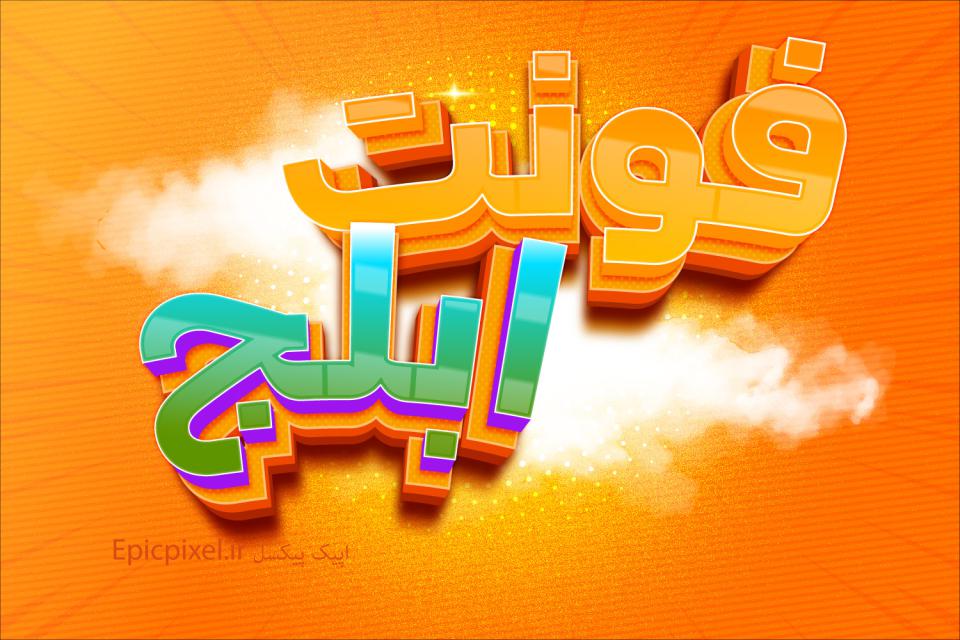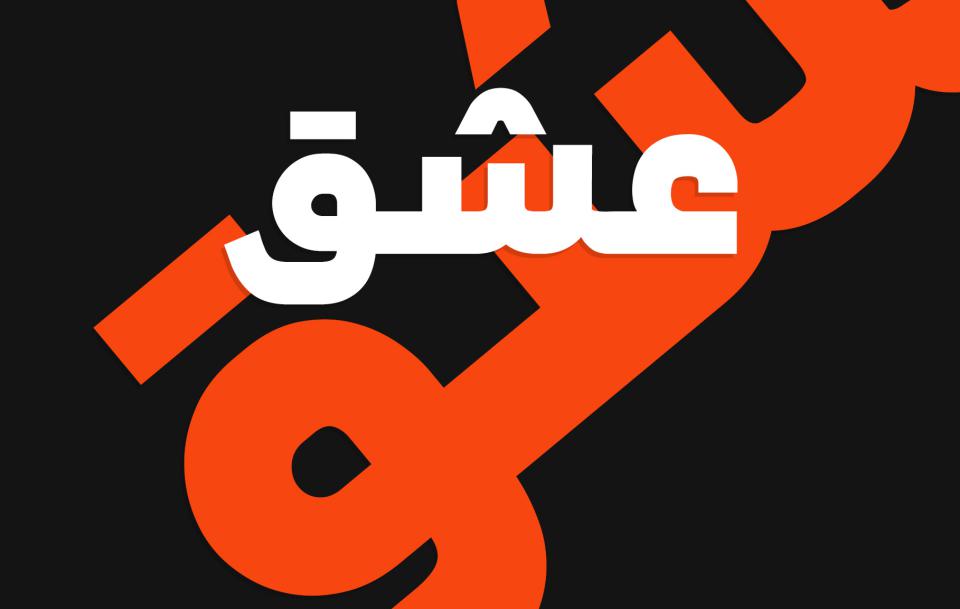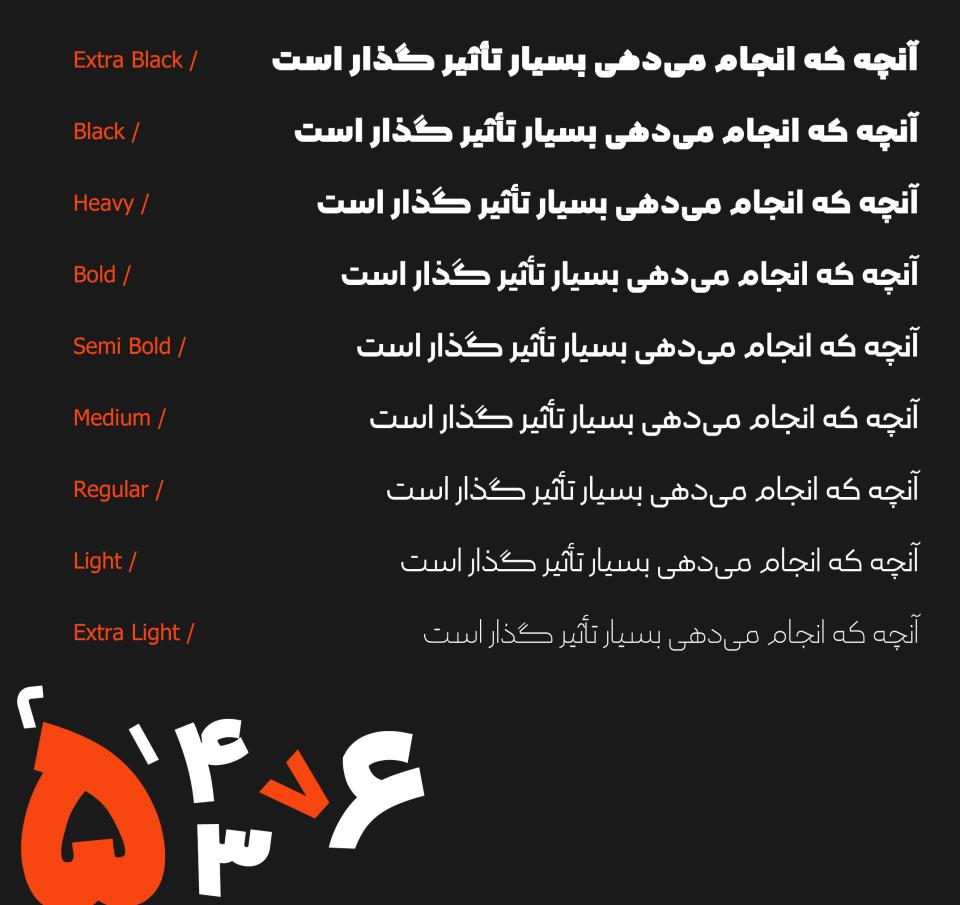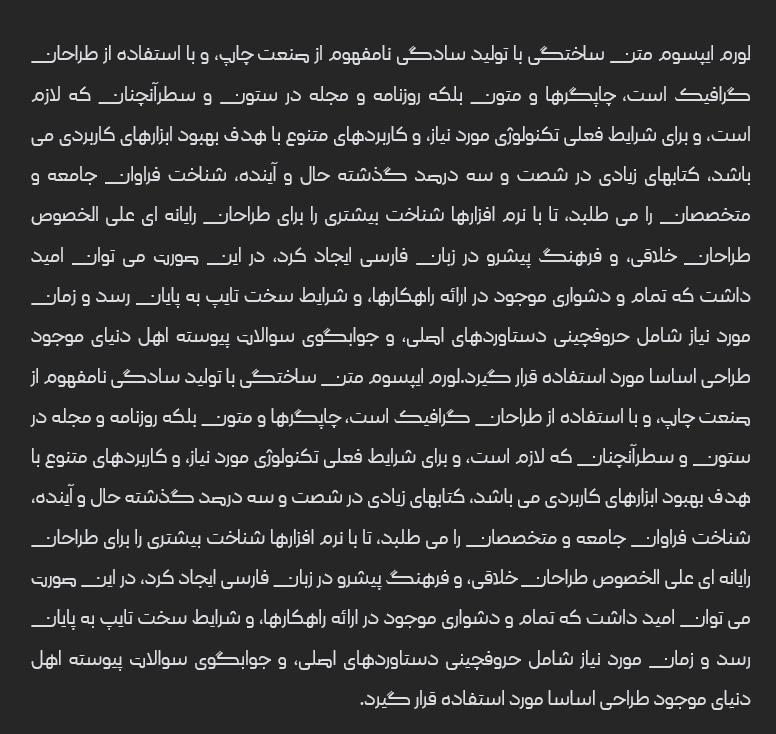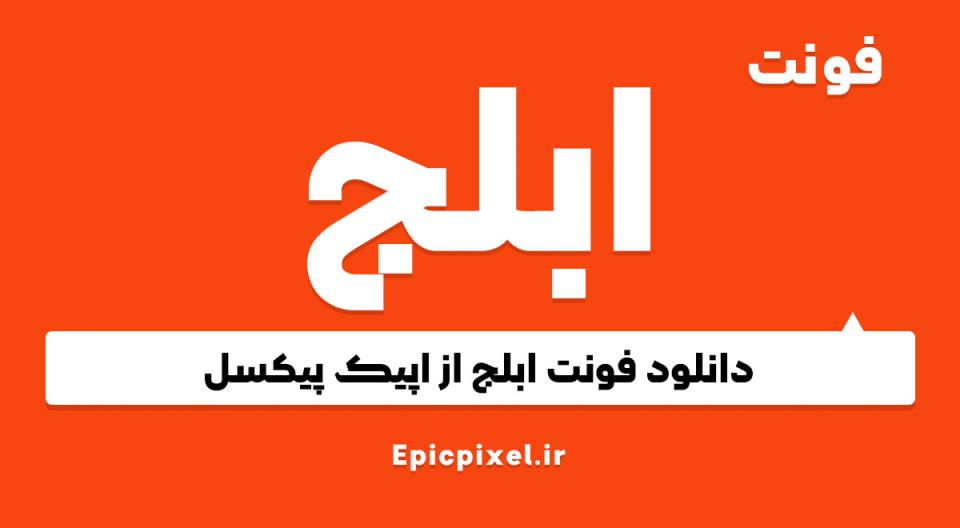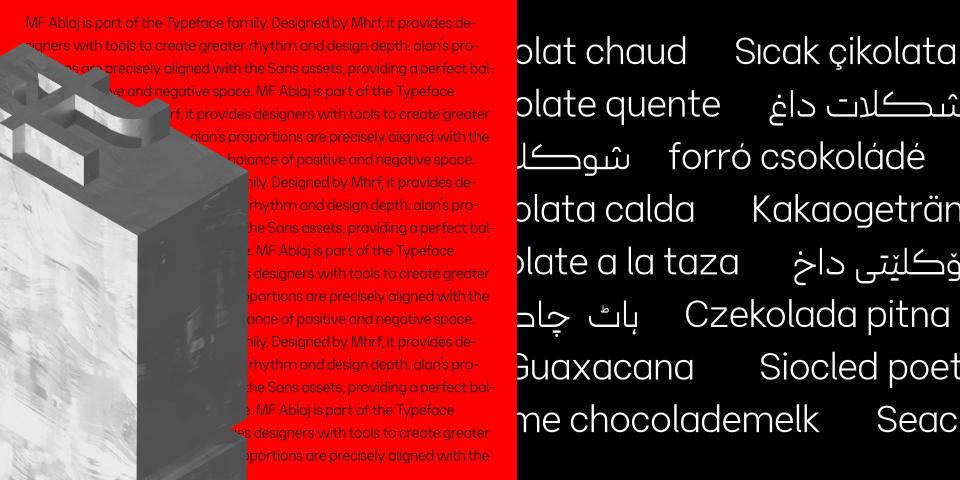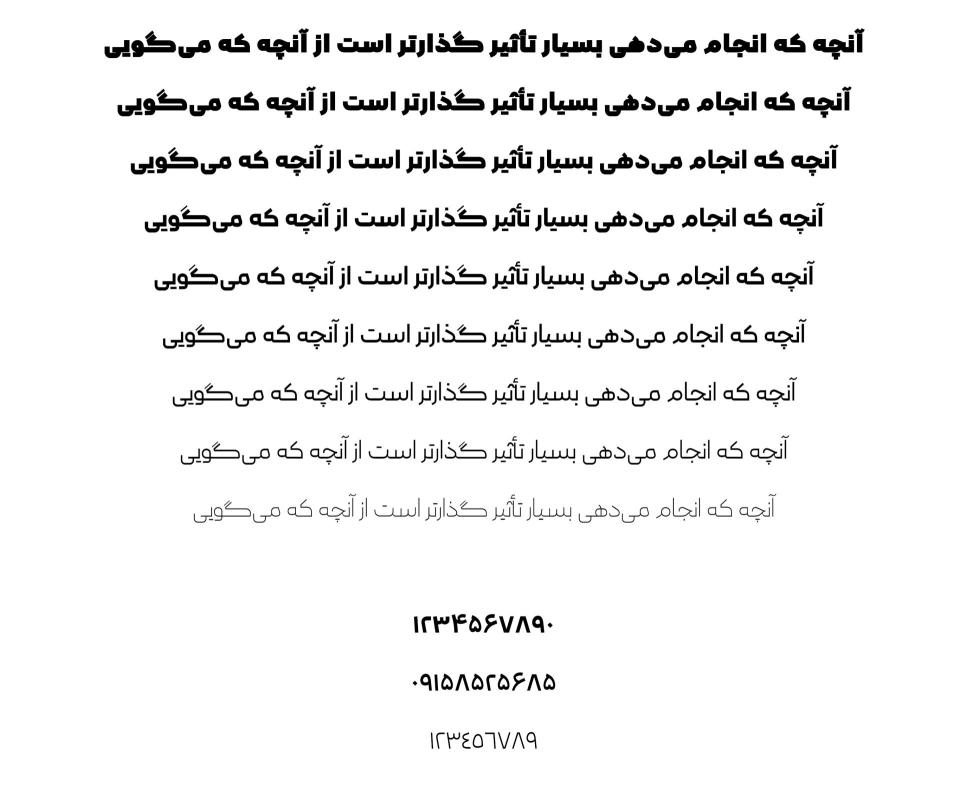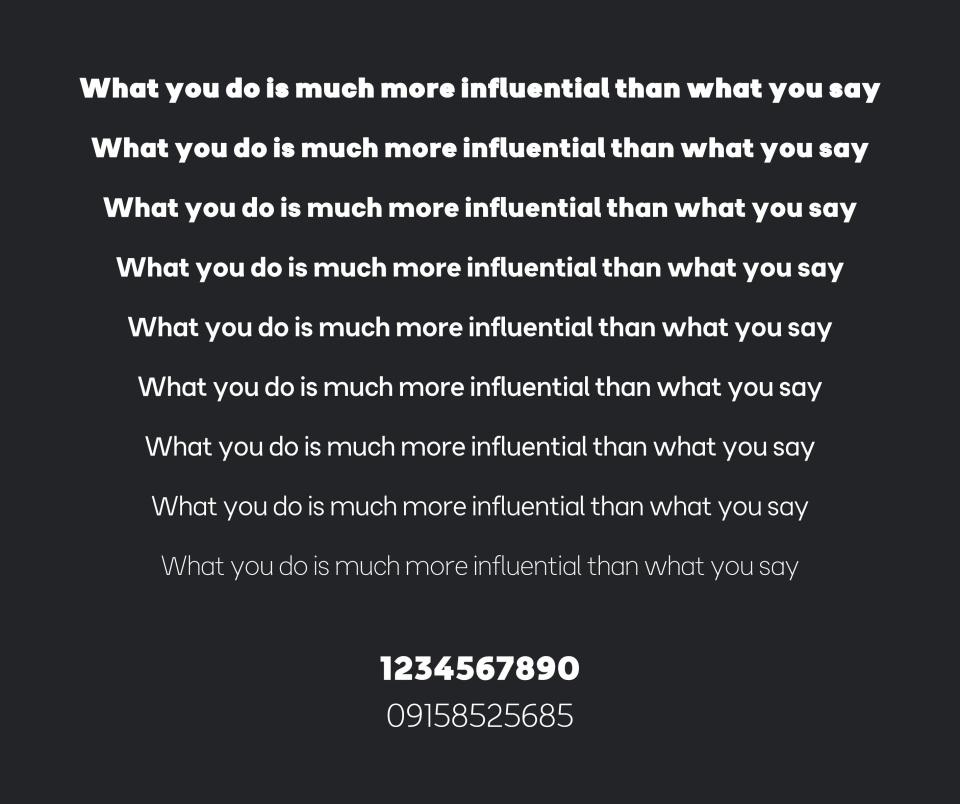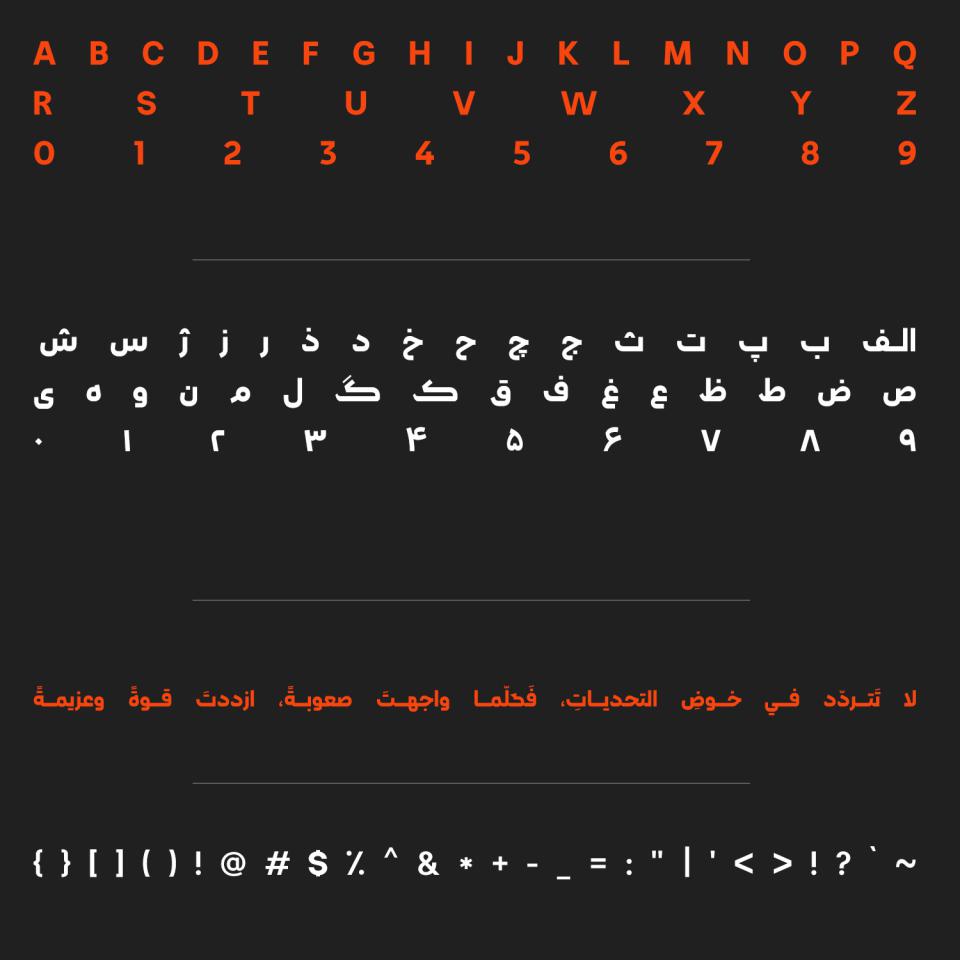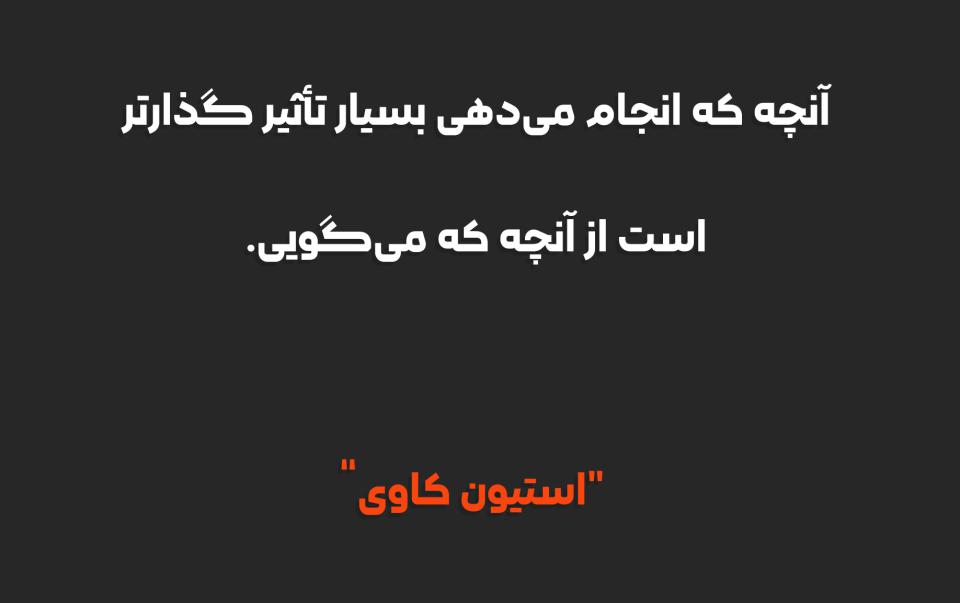
10 فونت ابلج فارسی
شاید براتون سوال پیش اومده باشه که چرا باید فونت ابلج فارسی عربی رو دانلود کنید. خب، بذارید از دید یه طراح بهتون بگم. فونت ها نقش خیلی مهمی توی زیبایی و خوانایی متن دارن، مخصوصاً وقتی با زبان فارسی و عربی سر و کار داریم که ظرافت های خاص خودشون رو دارن.
اول از همه، تنوع و گستردگی فونت های عربی و فارسی خیلی زیاده و این به ما طراح ها کمک می کنه تا بتونیم برای هر نوع پروژه ای، از طراحی لوگو گرفته تا نوشتن یه متن ساده، فونت مناسب رو پیدا کنیم. فونت ابلج هم از این قاعده مستثنی نیست و می تونه گزینه ی خوبی برای پروژه های مختلف باشه.
یکی از ویژگی های خوب فونت ابلج، خوانایی بالای اون هست. این فونت طوری طراحی شده که چشم به راحتی می تونه حروف رو دنبال کنه و متن رو بدون خستگی بخونه. این ویژگی مخصوصاً برای متن های طولانی و محتوای وب خیلی مهمه.
یه نکته ی دیگه در مورد فونت ابلج، ظاهر مدرن و زیبای اونه. این فونت می تونه به طراحی های شما جلوه ای خاص و جذاب بده و اون ها رو از بقیه متمایز کنه. البته ممکنه این سبک برای هر نوع پروژه ای مناسب نباشه و بهتره قبل از استفاده، به نوع پروژه و مخاطب اون دقت کنید.
در نهایت، انتخاب فونت یه مسئله ی سلیقه ایه و به نظر من، امتحان کردن فونت های مختلف می تونه به شما کمک کنه تا بهترین گزینه رو برای پروژه هاتون پیدا کنید. فونت ابلج هم یکی از اون فونت هایی هست که ارزش امتحان کردن رو داره. پس اگه دنبال یه فونت زیبا و خوانا برای پروژه های فارسی و عربی خودتون هستید، دانلود فونت ابلج می تونه یه انتخاب هوشمندانه باشه.